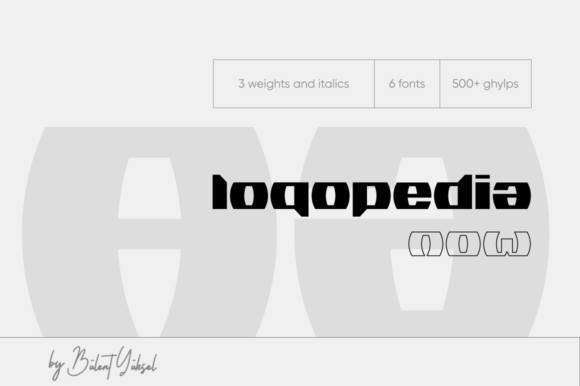
Creativefabrica Logopedia Now Font
[Creativefabrica] Logopedia Now Font
Logopedia Now - это геометрический и крутой шрифт для отображения.
Он отмечает абстрактные формы во всем их эклектическом блеске.